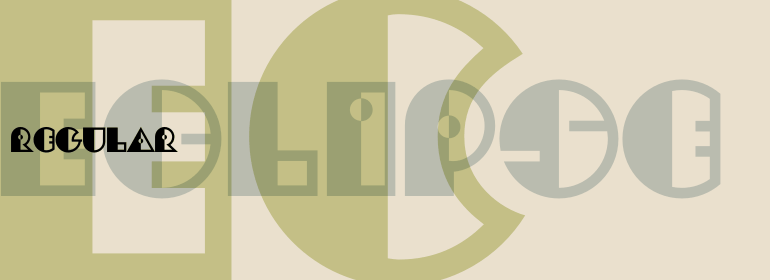
Eclipse™
Eclipse™,这款字体结构工整、笔画清晰,兼顾美观与易读性,适用于标题、正文、海报、包装、LOGO 等多种场景。字形优雅稳定,风格百搭耐看,适配日常排版与创意设计,让文字呈现更舒适、更具质感。Eclipse™一笔一画,皆是细节,以均衡的比例、流畅的线条打造舒适视觉体验,字形端正大气,风格简约现代。无论是商业设计、品牌宣传还是日常排版,都能轻松驾驭,让文字更有格调与力量。Eclipse™字体下载。